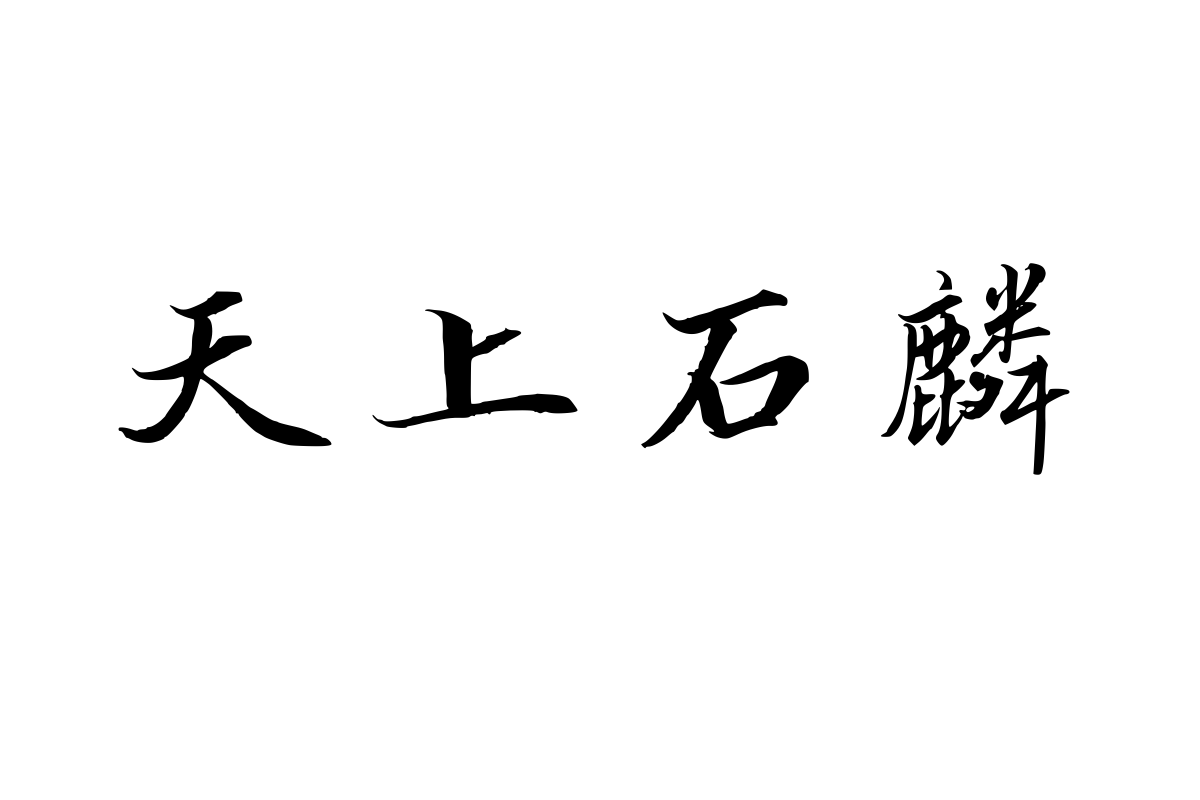
兰米繁华寂静字体是一套具有独特风格的中文字体,由著名设计师张海翔设计。这套字体以其独特的艺术风格和细腻的笔触而受到广泛赞誉。兰米繁华寂静字体采用了现代简约的设计思路,线条流畅、结构清晰,给人一种宁静而优雅的感觉。
在字形上,兰米繁华寂静字体采用了传统的汉字书写方式,但又融入了一些现代元素,使得整体风格更加独特。每个字的笔画都经过精心设计,既有力度又不失柔美,展现出一种独特的美感。
兰米繁华寂静字体适用于各种场合,无论是用于网页设计、广告宣传还是书籍封面,都能展现出其独特的魅力。此外,这套字体还具有较高的可读性和辨识度,适合用于印刷品和数字媒体。